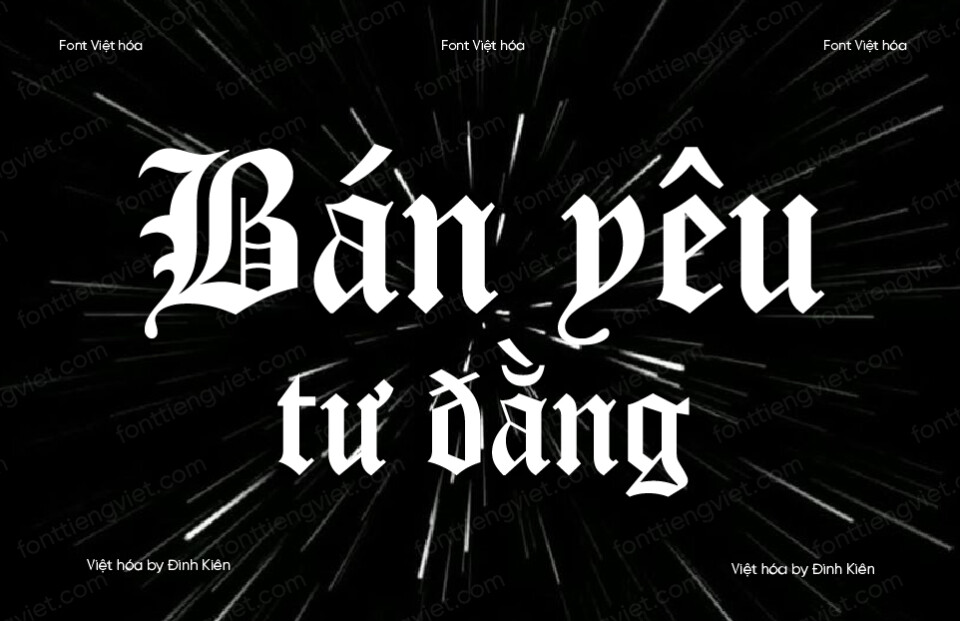
Trong thế giới thiết kế đồ họa và in ấn, đặc biệt là trong lĩnh vực giáo dục, việc lựa chọn một Font Chữ phù hợp cho các văn bằng, chứng chỉ là vô cùng quan trọng. Một font chữ không chỉ cần đẹp mắt mà còn phải đảm bảo tính chuyên nghiệp, dễ đọc và tương thích tốt với tiếng Việt. Đây chính là lúc Font Việt hóa UTM Diploma phát huy vai trò của mình. Với sự kết hợp hoàn hảo giữa tính thẩm mỹ và khả năng hỗ trợ tiếng Việt đầy đủ, UTM Diploma đã trở thành sự lựa chọn hàng đầu cho các trường học, cơ sở đào tạo và cá nhân khi muốn tạo ra những văn bằng, chứng chỉ chất lượng cao, mang đậm dấu ấn cá nhân và sự trang trọng cần thiết. Bài viết này sẽ đi sâu vào những ưu điểm nổi bật, cách sử dụng hiệu quả và lý do tại sao bạn nên chọn font chữ này cho các dự án quan trọng của mình, đặc biệt là cho các kỳ thi tốt nghiệp và các loại bằng cấp đòi hỏi sự chính xác và trang nghiêm.
Nhu cầu về một font chữ chuẩn cho các tài liệu học đường, bằng cấp và chứng nhận ngày càng tăng cao. Không chỉ dừng lại ở việc đảm bảo thông tin được truyền tải rõ ràng, font chữ còn góp phần tạo nên ấn tượng đầu tiên về chất lượng và uy tín của tổ chức cấp bằng. Chính vì lẽ đó, sự xuất hiện của Font Việt hóa UTM Diploma như một giải pháp toàn diện đã được đông đảo cộng đồng thiết kế và giáo dục đón nhận nồng nhiệt. Font này không chỉ giải quyết triệt để vấn đề về lỗi font tiếng Việt mà còn mang lại một vẻ đẹp cổ điển nhưng không kém phần hiện đại, rất phù hợp với bối cảnh giáo dục hiện nay.
Giới thiệu tổng quan về Font Việt hóa UTM Diploma
Bộ font UTM, viết tắt của “UTM Fonts”, là một trong những bộ font Việt hóa phổ biến và được yêu thích nhất tại Việt Nam. Nó bao gồm nhiều kiểu chữ khác nhau, phục vụ đa dạng các mục đích sử dụng. Trong số đó, UTM Diploma nổi bật với thiết kế serif cổ điển, mạnh mẽ và sang trọng. Chữ “Diploma” trong tên gọi đã ngụ ý rõ ràng về mục đích sử dụng chính của font này: dành cho các loại văn bằng, chứng chỉ, bằng tốt nghiệp, và các tài liệu chính thức khác. Sự tinh tế trong từng nét chữ, độ dày và khoảng cách được cân chỉnh hợp lý, tất cả tạo nên một tổng thể hài hòa, dễ đọc và mang tính thẩm mỹ cao. Điều đặc biệt quan trọng là Font Việt hóa UTM Diploma đã được tối ưu hóa hoàn toàn để hiển thị tiếng Việt một cách chuẩn xác, không gặp phải các lỗi dấu hay mã hóa ký tự thường thấy ở nhiều font chữ quốc tế không được Việt hóa.
Việc Việt hóa font chữ không chỉ đơn thuần là thêm các ký tự dấu mà còn là quá trình điều chỉnh khoảng cách, độ cao của dấu so với chữ cái gốc, đảm bảo tính thẩm mỹ và khả năng đọc tốt nhất. UTM Diploma đã hoàn thành xuất sắc nhiệm vụ này, mang đến một phiên bản tiếng Việt hoàn chỉnh và chuyên nghiệp. Nó không chỉ là một công cụ mà còn là một yếu tố góp phần nâng cao giá trị của các tài liệu giáo dục, từ cấp trung học phổ thông đến đại học và sau đại học. Đây thực sự là một lựa chọn đáng cân nhắc cho những ai đang tìm kiếm sự hoàn hảo trong từng chi tiết của văn bản.
Tại sao Font Việt hóa UTM Diploma lại được ưa chuộng?
Có nhiều lý do khiến Font Việt hóa UTM Diploma trở thành lựa chọn hàng đầu cho các chuyên gia thiết kế và các tổ chức giáo dục:
- Tính chuyên nghiệp và trang trọng: Với thiết kế serif cổ điển, UTM Diploma toát lên vẻ trang nghiêm và uy tín, rất phù hợp với những tài liệu quan trọng như bằng cấp, chứng nhận tốt nghiệp hay các thông báo chính thức.
- Hỗ trợ tiếng Việt đầy đủ và chuẩn xác: Đây là điểm cộng lớn nhất. Người dùng không còn phải lo lắng về việc font bị lỗi dấu, mất dấu hoặc hiển thị không đúng chuẩn Unicode. Mọi ký tự tiếng Việt đều được hiển thị một cách hoàn hảo, đảm bảo tính toàn vẹn của nội dung.
- Dễ đọc và rõ ràng: Dù mang phong cách cổ điển, UTM Diploma vẫn đảm bảo tính dễ đọc. Các nét chữ rõ ràng, khoảng cách giữa các chữ và dòng được thiết kế khoa học, giúp người đọc dễ dàng tiếp thu thông tin mà không bị mỏi mắt, ngay cả khi đọc trên các văn bằng có kích thước nhỏ.
- Tính thẩm mỹ cao: Sự cân đối trong từng con chữ, sự tinh tế trong các đường nét thanh mảnh và đậm đã tạo nên một vẻ đẹp hài hòa, sang trọng. Điều này giúp các văn bằng, chứng chỉ trở nên bắt mắt và ấn tượng hơn.
- Đa dạng ứng dụng: Mặc dù tên gọi chỉ ra mục đích chính, UTM Diploma vẫn có thể được sử dụng linh hoạt cho nhiều mục đích khác như thiết kế tiêu đề sách báo, thiệp mời cao cấp, các ấn phẩm đòi hỏi sự tinh tế và trang trọng. Sự linh hoạt này làm tăng giá trị sử dụng của font chữ.
Ứng dụng thực tiễn của Font Việt hóa UTM Diploma trong giáo dục và đời sống
Font Việt hóa UTM Diploma mang lại giá trị to lớn trong nhiều lĩnh vực, đặc biệt là giáo dục. Đầu tiên và quan trọng nhất, nó là lựa chọn lý tưởng cho việc thiết kế bằng tốt nghiệp, chứng chỉ hoàn thành khóa học, chứng nhận học sinh giỏi hay các văn bằng danh dự. Một tấm bằng được in với font chữ đẹp, chuyên nghiệp không chỉ thể hiện sự tôn trọng đối với người nhận mà còn phản ánh chất lượng và sự nghiêm túc của tổ chức cấp bằng. Đối với các trường học từ cấp mầm non đến đại học, việc sử dụng một bộ font thống nhất và chất lượng cao như UTM Diploma cho tất cả các tài liệu chính thức sẽ góp phần xây dựng hình ảnh thương hiệu mạnh mẽ và uy tín.
Bên cạnh đó, font chữ này còn được ứng dụng trong việc thiết kế các giấy mời dự lễ tốt nghiệp, kỷ yếu học sinh, hay các báo cáo nghiên cứu khoa học cần sự trang trọng. Trong đời sống, những cá nhân có nhu cầu tự tay thiết kế thiệp mời đám cưới, thiệp sinh nhật cao cấp hoặc các ấn phẩm mang tính cá nhân hóa cũng có thể tận dụng vẻ đẹp của UTM Diploma để tạo ra sản phẩm độc đáo, ấn tượng. Sự dễ đọc của font cũng giúp cho các thông tin quan trọng trên văn bằng, chứng chỉ được hiển thị rõ ràng, không gây nhầm lẫn hay khó khăn cho người đọc. Đây là một yếu tố then chốt, đặc biệt trong các tài liệu pháp lý hoặc hành chính liên quan đến kết quả học tập của học sinh và sinh viên.
Tóm lại, Font Việt hóa UTM Diploma không chỉ là một lựa chọn thông thường mà còn là một khoản đầu tư thông minh cho bất kỳ ai đang tìm kiếm sự hoàn hảo trong việc thiết kế các văn bằng, chứng chỉ, hoặc tài liệu cần sự trang trọng và chuyên nghiệp. Với khả năng hỗ trợ tiếng Việt xuất sắc, thiết kế tinh tế và tính ứng dụng cao, UTM Diploma xứng đáng là “người bạn đồng hành” đáng tin cậy. Đảm bảo rằng mọi thông điệp quan trọng của bạn được truyền tải một cách rõ ràng, đẹp mắt và không mắc lỗi chính tả. Hãy trải nghiệm sự khác biệt mà Font Chữ này mang lại để nâng tầm giá trị cho các sản phẩm in ấn của bạn, từ các bằng cấp dành cho học sinh, sinh viên cho đến các chứng chỉ chuyên môn cao.